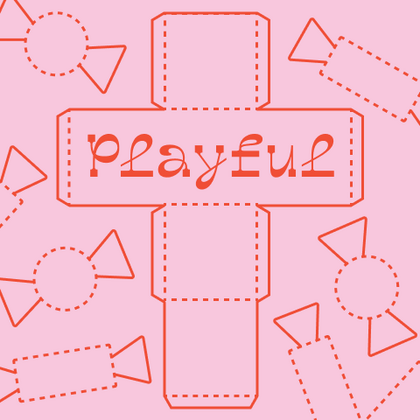
Игривые шрифты
TT Turns — ТТ Тернс
Произносится «ТТ Тернс». «Turns» — производное слово от turn, в переводе с английского «поворот». Буквы «TT» являются аббревиатурой названия компании.
TT Frantz — ТТ Франтц
Произносится «ТТ Франтц». «Frantz» — имя собственное немецкого происхождения. Буквы «TT» являются аббревиатурой названия компании.
TT Modernoir — ТТ Модернуар
Произносится «ТТ Модернуар». «Modernoir» — производное слово от moderne (с французского «современный») и noir (с французского «чёрный»). Буквы «TT» являются аббревиатурой названия компании.
TT Marks — ТТ Маркс
Произносится «ТТ Маркс». «Marks» — множественное число мужского имени Mark. Шрифт назван в честь сына соавтора шрифта. Буквы «TT» являются аббревиатурой названия компании.
TT Gentlemens — ТТ Джентльменс
Произносится «ТТ Джентльменс». «Gentlemens» — производное слово от Gentlemen, в переводе с английского «джентельмены». Буквы «TT» являются аббревиатурой названия компании.
TT Ramillas — ТТ Рамильяс
Произносится «ТТ Рамильяс». «Ramillas» — производное слово от испанского «ramilla», что переводится как «стебель» . Это название отражает визуальные особенности шрифта: тонкие, изящные, расширяющиеся к концам засечки, напоминающие веточки . Буквы «TT» являются аббревиатурой названия компании.
TT Gertika — ТТ Гертика
Произносится «ТТ Гертика». Слово «Gertika» является неологизмом. Буквы «TT» являются аббревиатурой названия компании.
TT Biersal — ТТ Бьерсал
Произносится «ТТ Бьерсал». «Biersal» образовано от немецкого Bieresel — имени домашнего духа из мифологии. Буквы «TT» являются аббревиатурой названия компании.
TT Paplane — ТТ Паплэйн
Произносится «ТТ Паплэйн». «Paplane» — производное слово от paper (с английского «бумага») и plane (с английского «самолёт»). Буквы «TT» являются аббревиатурой названия компании.
TT Carvist — ТТ Карвист
Произносится «ТТ Карвист». «Carvist» — производное слово от carving, в переводе с английского «вырезание». Буквы «TT» являются аббревиатурой названия компании.
TT Trailers — ТТ Трейлерс
Произносится «ТТ Трейлерс». «Trailers» — производное слово от trailer, в переводе с английского «трейлер». Буквы «TT» являются аббревиатурой названия компании.
TT Marxiana — ТТ Марксиана
Произносится «ТТ Марксиана». «Marxiana» — производное слово от имени собственного «Маркс». Шрифт назван в честь Адольфа Фёдоровича Маркса — основателя типографии и издательства, выпускавшего в Санкт-Петербурге журнал «Нива», шрифты из которого были взяты за основу при создании этой гарнитуры . Буквы «TT» являются аббревиатурой названия компании.
TT Geekette — ТТ Гикетт
Произносится «ТТ Гикетт». «Geekette» — производное слово от geek (с английского «гик», человек, увлеченный технологиями) и уменьшительного женского суффикса -ette. Буквы «TT» являются аббревиатурой названия компании.
TT Alientz — ТТ Элиенц
Произносится «ТТ Элиенц». «Alientz» — производное слово от Alien, в переводе с английского «пришелец». Буквы «TT» являются аббревиатурой названия компании.